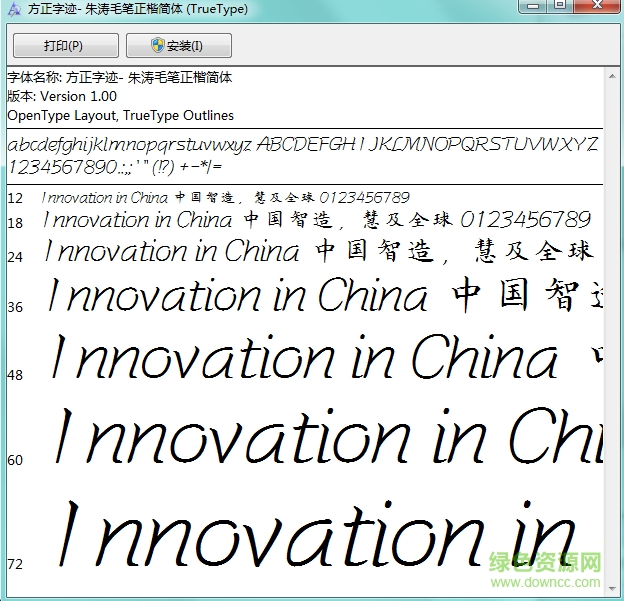
方正字跡朱濤毛筆正楷簡體
朱濤毛筆正楷方正字跡聯(lián)合推出的一款毛筆字體,字跡精簡端正,有著質(zhì)樸和清秀之風(fēng),文字干練流暢,有著很好的觀賞體驗(yàn),來綠色資源網(wǎng)免費(fèi)擁有吧!
方正字跡-朱濤毛筆正楷簡體介紹
朱濤毛筆正楷體是一款手寫風(fēng)格的硬筆書法字體,字體簡潔大方,字形端正。適合名片設(shè)計(jì)、包裝設(shè)計(jì)等廣告設(shè)計(jì)場合使用。
朱濤毛筆正楷體簡體
朱濤毛筆小編點(diǎn)評(píng)
朱濤毛筆正楷字體以楷體字為原形而設(shè)計(jì),線條粗細(xì)適中,筆畫平直,字庫完整,整體效果非常出色,可運(yùn)用在海報(bào)設(shè)計(jì)、廣告創(chuàng)意等諸多場合!